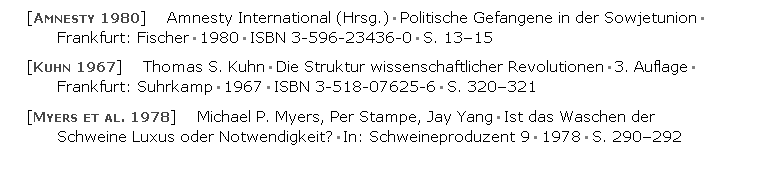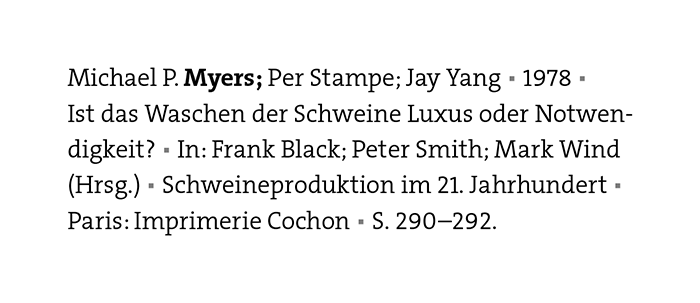
Interpunktion und Typografie in Titelangaben (Literaturbelege)
Im Oktober letzten Jahres trat die DIN ISO 690 (Information und Dokumentation –Richtlinien für Titelangaben und Zitierung von Informationsressourcen) in Kraft.
Sie ersetzt DIN 1505-2:1984-01 (Titelangaben von Dokumenten; Zitierregeln).
ISO 690 gibt explizit keine Empfehlungen zur Interpunktion und Typografie.
Mich interessiert Eure Lieblingsvariante. Welche (Trenn)Zeichen setzt ihr an welcher Stelle, wo greift ihr typische Konventionen auf, wo brecht ihr sie?
Kennt ihr gute Übersichten im Netz, wo verschiedene Systeme der Interpunktion gegenübergestellt werden?
Meine eigenen Überlegungen sind noch nicht weit gediehen. Nicht zuletzt, weil ich selten mit Titelangaben zu tun habe (bin kein Profi, anders als die meisten hier im Forum).
Den Punkt  als Trennzeichen von Elementen in Titelangaben z.B. mochte ich selber nie gern.
Ebensowenig das Komma zwischen Autoren, da es auch zwischen Nachname und Vorname steht.
Oder den Wechsel der Reihenfolge von Vorname und Nachname.
Oder ein "und" vor dem letzten Autor.
Anführungszeichen als Kennzeichnung eines Elementes finde ich hässlich.
etc.
MYERS, Michael P., Jay YANG, und Per STAMPE. Visualization and functional analysis of
a maxi-K channel (mSlo) fused to green fluorescent protein (GFP). ...
MYERS, Michael P. ; YANG, Jay ; STAMPE, P. | Visualization and functional analysis of
a maxi-K channel (mSlo) fused to green fluorescent protein (GFP) | ...
Na ja, so ein Verkettungszeichen als Trennzeichen ist sicher nicht der Weisheit letzter Schluss. Das ist nur ein Beispiel.
Im wissenschaftlichen Kontexten interessiert man sich nicht für DIN, da hat man eigene, gewachsene Verfahren. Die Juristen zitieren anders als die Historiker als die Biologen. Die Deutschen anders als die englischsprachigen, Zeitschrift A anders als Reihe B, ... Und da die Wissenschaftler Gewohnheitstiere sind, werden sie durch zu große Abweichungen vom Gewohnten stark irritiert. Kurzum: Ich zitiere nach der aktuellen Gepflogenheit der Zielgruppe.
Was ich jedoch in jedem Fall häßlich finde, ist die Angewohnheit einiger, Nachnamen in Versalien zu setzen. Für solche Verwendungsfälle bieten sich Kapitälchen an. Den Titel setze ich kursiv, was die Übersicht, insbesondere bei sehr langen Literaturlisten, erhöht.
Bei völliger Freiheit bei Quellenangaben nehme ich das, was mir in diesem Kontext schön aussieht. Ausreichende Strukturierung erreiche ich gerne mit einem Kolon (U+0387) oder Mittelpunkt (U+00B7), welche mir weniger aufdringlich erscheinen als der senkrechte Strich.
Deinem Argument für homogene Zielgruppen folge ich.
Wir geben mit Freunden ein nicht-kommerzielles Fahrradmagazin heraus, welches ab und an auch Artikel mit wissenschaftlichem Hintergrund enthält. Die Fachgebiete jedoch sind verschieden. Medizin, Technik, Verkehrsplanung, ... Um nur einige aufzuzählen.
Kurz: wir haben alle Freiheiten, eine eigene Konvention für die Titelangaben zu entwickeln.
Zu "Nachnamen in Versalien" stimme ich voll zu. Kann ich auch gar nicht leiden. Im Posting oben habe ich sie nur deshalb verwendet, weil man in einem Forenposting meines Wissens nach keine Kapitälchen darstellen kann.
U+0387 empfinde ich selber als zu dezent. Hans-Peter Willberg schreibt in "Lesetypo" auf Seite 225 dazu: "Der Punkt auf der Mitte in der Fette der Grundschrift bringt Unruhe in die Zeile und ist schwer aufzufinden: ein ungeeignetes Mittel."
Ein gegliedertes Literaturverzeichnis, welches als Haupttrennzeichen (also von Gruppen innerhalb einer Titelangabe) etwas Anderes als den Punkt verwendet habe ich freier Wildbahn noch nicht gesehen. Was nix heißen muss. Ihr kennt sicher sehr viel mehr Stile als ich.
Hier nochmal eine Sammlung einiger Gedanken von mir zum Thema:
1. "Vorname Nachname" statt "Nachname, Vorname" (unter Beibehaltung der Sortierung nach Nachname)? Ich kann jedenfalls Namen in der Form "Vorname Nachname" deutlich besser erfassen
2. Wenn "Nachname, Vorname", dann "; " als Trennzeichen, weil der Punkt hinter einem Initial gefolgt von einem Komma häßlich ist?
3. Kein "und" oder "&" vor dem letzten Autorenahmen?
4. Jahr direkt hinter dem letzten Autor? (Insbesondere, wenn man die Zitierung [Autor Jahr] einsetzt.)
5. Onlinequelle bei Veröffentlichung als Webseite hinter dem Artikelnamen als Linktext? Oder doch extra als URL?
6. Vor einem Sammelband oder einer Zeitschrift den Bezeichner "In: "? Ich neige dazu.
7. Soll "[Autor Jahr]" im Literaturverzeichnis auch jeder Titelangabe voranstehen, damit das Auge es besonders leicht hat - oder ist das zuviel Redundanz?
8. Kein Punkt ganz am Ende der Titelangabe?
9. Zwei Blöcke, die einem Doppelpunkt folgen und zwischen denen kein anderes Trennzeichen steht finde ich hässlich.
Beispiel:
In: Bolc, L. (ed.): Natural Language Communication with Computers.
Heftnummer: Leider gibt es Zeitschriften, bei denen die Heftnummer wichtig ist. Mehrheitlich werden bei wissenschaftlichen Zeitschriften ja alle Hefte eines Jahrgangs durchgängig paginiert, d.h. Bandzahl und Seitenzahlen reichen. Manchmal werden aber Hefte auch einzeln gezählt. Und dann kann es passieren, dass die Angabe "3 (2013), 17–35" auf 12 verschiedene Hefte des einen Jahrgangs zutreffen kann.